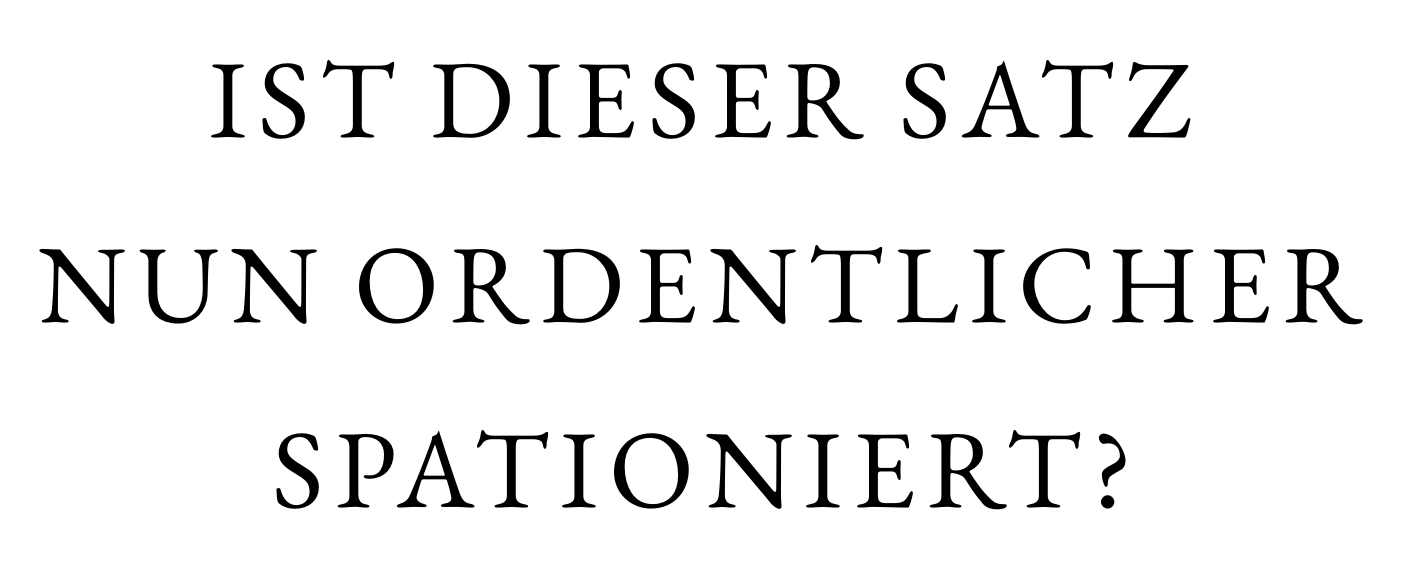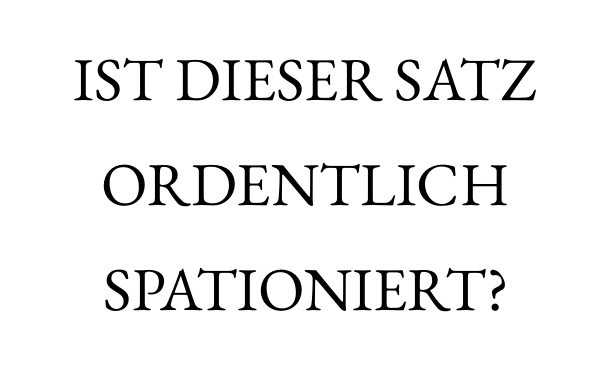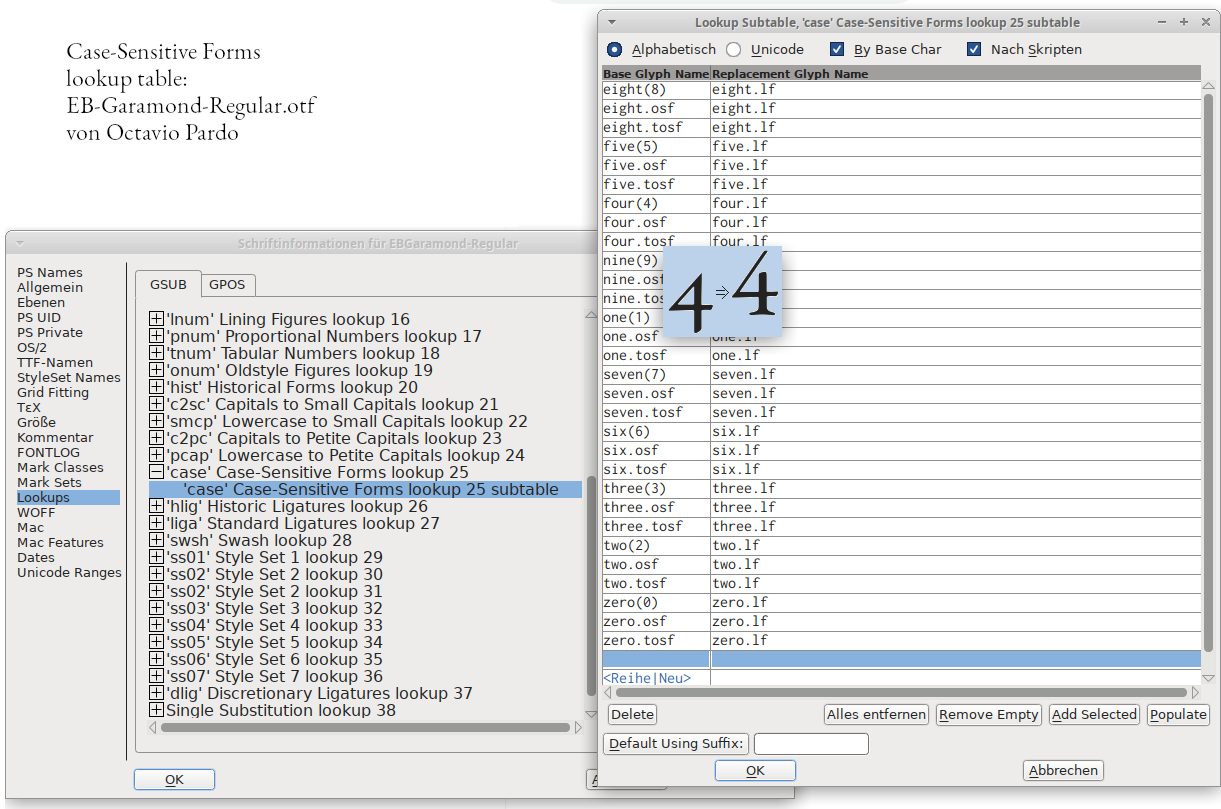
Suche Spationierungstabelle für Versalien der EB Garamond von Octavio Pardo
da unerfahren in der Spationierung von Versalien, wäre mir eine Spationierungstabelle für Versalien der EB Garamond (in der Regular-Fassung von Octavio Pardo, also EBGaramond-Regular.otf) hilfreich.
Grund meiner Bitte: Ich wurde vor einiger Zeit von Typografie-Kundigen angesprochen, eine von mir aus Versalien gesetzte Überschrift doch bitte optisch gleichmäßiger zu spationieren. Die Aufgabe ließ sich damals in geduldiger Zusammenarbeit lösen, zurück blieb aber meine Unsicherheit, warum das (nach längerem Probieren und Korrigieren) gefundene Ergebnis schließlich als gut befunden wurde.
Nun lese ich diesen Artikel von Oliver Schöndorfer – und bin so beeindruckt wie erschrocken über die Komplexität des Themas für jemanden wie mich als Typografie-Laien:
»Ausgleich und Spationierung
Maßnahmen zur Harmonisierung
von Versalzeilen«
Ideal wäre für mich daher eine fertige Versalien-Spationierungstabelle, entweder für die EB Garamond, oder notfalls für die Adobe Garamond Pro, die ihr ja sehr ähnelt.
Alternativ würde mir auch ein Buchhinweis helfen, falls es ein Werk gibt, in dem ich lernen kann, wie ich Versalien-Paare und -Worte ›perfekt‹ spationiere.
Per FontForge fand ich Kerning-Informationen zu Versalien in der .otf-Datei. Dennoch wurde mir, nach Satz per LaTeX, die fehlende / bzw. nicht genügende Spationierung kritisiert.
Kann es sein, dass ich an falscher Stelle suchte, gibt es in den Fonts zusätzlich zum Kerning andere Spationierungsinfos für Versalien, die ich evtl. als OFT-Feature gesondert aktivieren müsste?
Oder bin ich auf einem Holzweg und die folgenden, automatisch gesetzten Zeilen sind korrekt spationiert?
automatisch gesetzten Zeilen sind korrekt spationiert
Für mein Gefühl nein. Aber Versalsatz gehört auch nicht zu den Normalfällen von Alltagsschriften. Ich habe zudem Zweifel, ob ein Algorithmus optische Ausgewogenheit berechnen kann, immerhin ist Gefühl nicht mathematisch erfassbar. Deswegen halte ich auch Tabellen mit festen Angaben nicht für wirklich tauglich, denn der Rhythmus einer Schrift ist zu sehr vom Gesamteindruck abhängig, als dass eine Tabelle dem gerecht werden könnte, denn auch eine Tabelle wird nur nur kleine Glyphengruppen berücksichtigen können und nicht das komplette, individuelle Umfeld. In dem Wikipedia-Artikel werden Pakete für Latex erwähnt: https://de.wikipedia.org/wiki/Sperrsatz
In Deinem Beispiel ist eine regelbasierte Sperrung nicht hilfreich, denn es geht ja nicht um eine mathematische Formulierung, sondern ausschließlich um den optischen Eindruck. Glyphen mit großen Innenräumen und Glyphen mit viel Luft um sich herum reißen da dann schnell Löcher in den Ausdruck.
Kann es sein, dass ich an falscher Stelle suchte, gibt es in den Fonts zusätzlich zum Kerning andere Spationierungsinfos für Versalien, die ich evtl. als OFT-Feature gesondert aktivieren müsste?
Technisch ist das möglich. Es gibt verschiedene CASE-Feature, die speziell auf Versalsatz ansprechen. (Allerdings nur, wenn der Versalsatz im Anwendungsprogramm angewählt wurde. Das bloße Eintippen von Großbuchstaben ist in technischer Hinsicht kein Versalsatz.)
Es ist aber nicht üblich, hier separates Kerning abzulegen. Man nutzt das eher für Dinge wie erhöhte Laufweite das generelle Anheben von Klammern und Satzzeichen.
Grundsätzlich ist Kerning immer ein Kompromiss für übliche Anwendungen. Herausgestellte Anwendungen wie Logos und Buch-Titel in Versalien werden manuell unterschnitten.
vor 43 Minuten schrieb khzimmer2:
Oder bin ich auf einem Holzweg und die folgenden, automatisch gesetzten Zeilen sind korrekt spationiert?
Verschiedene Designer würden wahrscheinlich verschiedene Antworten geben. Fakt ist, diese spezielle Schrift ist kein leichter Fall. Die erzeugten Weißräume unterscheiden sich stark, aber die Serifen lassen Unterschneidungen kaum zu. Die einfachste Lösung wäre die deutliche Erhöhung der Laufweite.
Wie im Eingangsposting erwähnt, ist mir die Theorie bekannt, mir geht es nun um die Umsetzung.
Ich formuliere mal so:
Wie finde ich (ohne Ausbildung als Typograf) für alle lateinischen Versalien der EB Garamond den optischen Beginn und das optische Ende, um für die entsprechenden Buchstaben-Paare die Spationierung richtig zu bekommen?
Um Schöndorfer (siehe oben verlinktes PDF) zu zitieren:
»Um Versalzeilen bis ins kleinste Detail zu harmonisieren, braucht es ein geschultes Auge, viel Zeit, Übung, Erfahrung und Hingabe. Aber auch dann werden die Ergebnisse oft unter Fachleuten noch diskutiert.«
Den zweiten Satz verstehe ich nicht. Wenn es die beschriebenen Regeln gibt (opt. Beginn/Ende suchen, dann auf mögl. gleich große Zwischenräume achten, dabei einige Innenräume (z.B. im E) aussparen), wieso lässt sich die Sache dann nicht in einer Tabelle der möglichen Buchstabenpaare festlegen, so dass es ab dann immer stimmt?
Wie man sieht ... leider vor allem englischsprachige Literatur ...